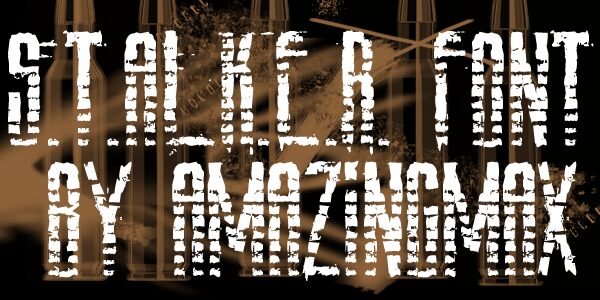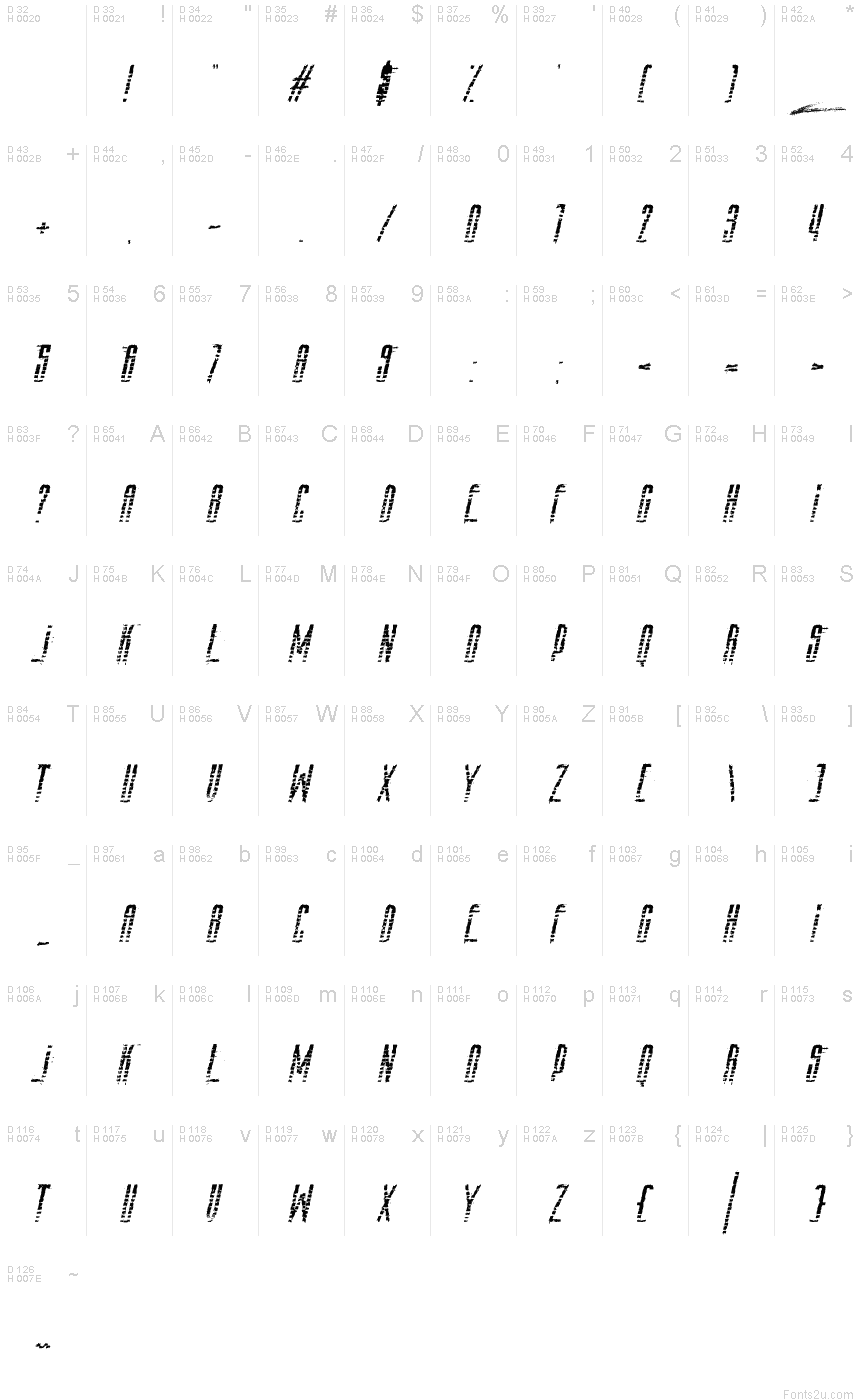
AmazS.T.A.L.K.E.R.Italic
Amaz S.T.A.L.K.E.R. Italic autorstwa Amazingmax to darmowy, erodowany krój szablonowy display, zbudowany z mocnych, pochylonych wersalików. Szerokie kształty liter są przełamane powtarzającymi się poziomymi cięciami i szorstkimi ubytkami, a fragmenty pociągnięć zredukowane są do wąskich szyn i metalowych odłamków. Pochylenie do przodu utrzymuje zniszczone kształty w ruchu.
Ekrany tytułowe gier to jego najsilniejsze środowisko, szczególnie w grach survival horror, akcji postapokaliptycznej czy industrialnym science-fiction. Jego poszarpana konstrukcja sprawdza się również na plakatach wydarzeń, w gadżetach i w brandingu rozrywkowym, ponieważ każde użycie może czerpać z tej samej atmosfery zagrożenia, rozkładu i wrogich maszyn.
Oparty na logo gry wideo S.T.A.L.K.E.R.